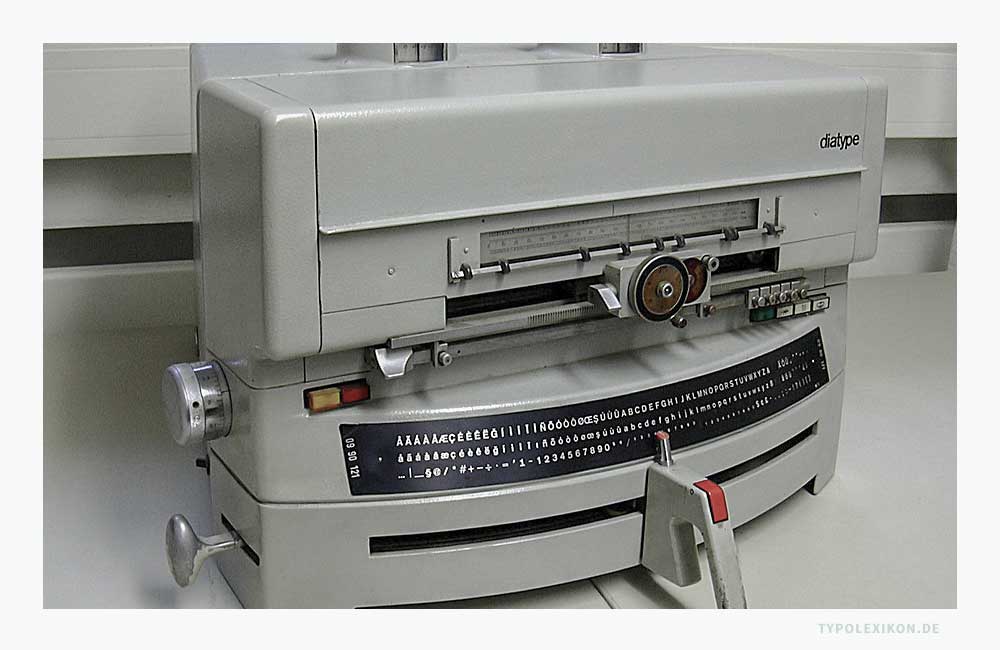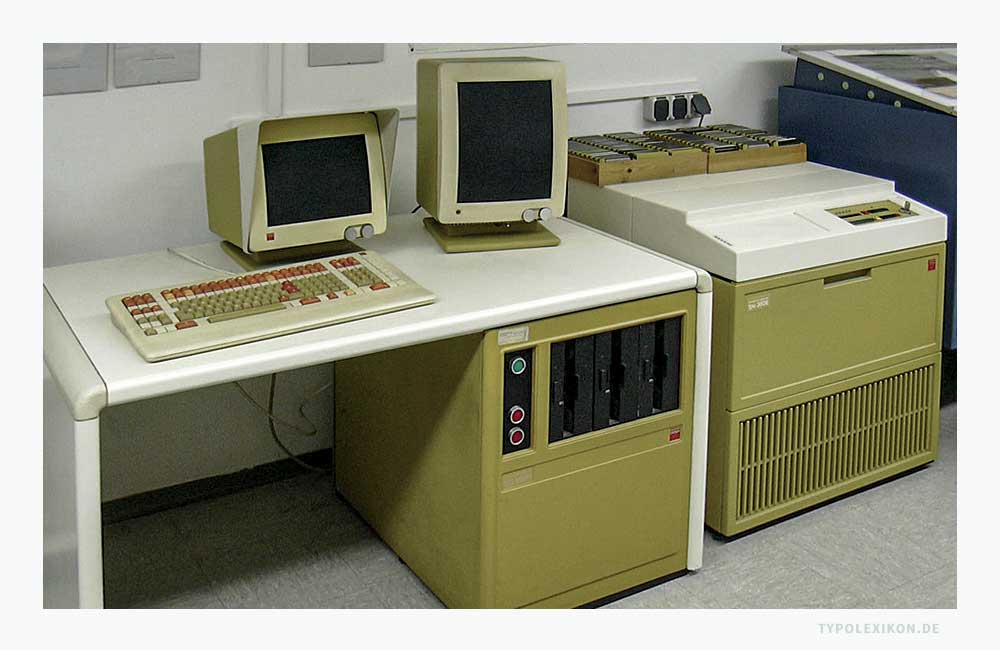
Fotosatz
»Fotosatz« ist eine ugs. Bezeichnung aus dem gewerblichen Sprachschatz dspr. Schriftsetzer und Drucker für den »Optomechanischen Lichtsatz«, einem Verfahren zur Schriftsatzherstellung; alternative Bezeichnung »Lichtsatz«.
Verkürzt formuliert, durchwandert bei optomechanischen, projektionsgesteuerten Fotosatzanlagen der von der Lichtquelle erzeugte Lichtstrahl ein System von Linsen, Spiegeln und Prismen eine Schablone mit der Schrift (Schriftbildträger), um dann auf Fotopapier oder Lithofilm (Abk. Litho) seitenrichtig für den Siebdruck oder seitenverkehrt für den Offsetdruck belichtet und im Anschluss im Nasslabor bzw. später in speziellen Entwicklungsmaschinen entwickelt zu werden. Mit diesen »Lithos« können dann Siebe für den Siebdruck oder Druckplatten für den Offsetdruck belichtet werden.
Fotosatz-Verbundsystem »tps 6300« (Texterfassung und Datenverwaltung) und »tpu 3608« (Belichtungseinheit) der Berthold GmbH. Quelle: Lehrdruckerei des Instituts für Buchwissenschaft, Johannes Gutenberg-Universität Mainz. Foto: Derivat Graph, 2007 gemeinfrei.
Die Belichtung auf einer Fotosetzmaschine erfolgt Schriftzeichen für Schriftzeichen, wobei die Schriftgrade durch Festoptiken oder später, ab den 1980er Jahren, stufenlos durch ein Zoomobjektiv wählbar waren. Ebenso konnten erstmals optomechanisch Zeilenabstände, Schriftlaufweiten, Schriftlagen, Schriftstärken und Schriftbreiten stufenlos verändert werden, was allerdings aus Sicht der Mikrotypografie zu qualitativ minderwertigen Satzergebnissen führte. Beispielsweise war es nun technisch möglich, Schriften optisch zu verzerren, zu dehnen, zu verdicken oder zu stauchen, was allerdings der Lesbarkeit und der Ästhetik in vielerlei Hinsicht nicht unbedingt förderlich war.
Mit der Einführung des Fotosatzes verzichteten weltweit Buch- und Zeitungsverlage auf die Verwendung von typografischen Ligaturen, denn diese waren technisch nun nicht mehr notwendig und der Werksatz wurde dadurch deutlich günstiger. Infolge veränderten sich auch die Lesegewohnheiten der Rezipienten.
Historie
Der Fotosatz wurde ursprünglich Ende des 19. Jahrhunderts für Flachdruckverfahren, speziell für den Tiefdruck und Offsetdruck entwickelt. Die ersten Patente erhielt 1893 der Engländer Arthur Ferguson und der 1894 der Ungar E. Porzsold. 1)
Die ersten Fotosetzmaschinen in Deutschland kamen Ende der 1950er Jahre zum Einsatz, beispielsweise die halbautomatische und mechanisches »Diatype« von Hugo Heine, die er zwischen 1952 und 1960 im Auftrag der Schriftgießerei H. Berthold AG (siehe Hermann Berthold) 2) entwickelt hatte und die 1958 – kurz vor dem hundertjährigen Jubiläum der H. Berthold AG – auf der Drupa in Düsseldorf, der weltgrößten Messe der Druck- und Druckmedienindustrie, vorgestellt wurde.
Fotosatzgerät Diatype der H. Berthold AG. Quelle: Lehrdruckerei des Instituts für Buchwissenschaft, Johannes Gutenberg-Universität Mainz. Foto: Derivat Graph, 2007 gemeinfrei.
In den nachfolgenden Jahren bis Ende der 1990er Jahre produzierten unterschiedliche Hersteller, unter ihnen auch die Linotype GmbH, 3) unterschiedliche Arten von Fotosetzmaschinen, die den materiellen Schriftsatz mit physischen Drucktypen aus Metall (z.B. aus einer Blei-Zinn-Antimon-Kupfer-Legierung) in der BRD (Westdeutschland), Österreich und der Schweiz ab den 1970er Jahren sukzessive ablösten und den Schriftsatz, die Druckvorstufe (Prepress) und das gesamte polygrafische Gewerbe (Druckwesen) revolutionierte und völlig neu strukturiere. Darüber hinaus brachte der Fotosatz für das Grafikdesign und Editorial Design mehr gestalterische Freiheiten und löste – außer in der DDR (Ostdeutschland) – den materiellen Schriftsatz nahezu komplett ab. Althergebrachte Berufe gingen verloren, völlig neue Berufsbilder, Maschinen und Firmen entstanden, so auch viele eigenständige Fotosetzereien.
Ab 1982 revolutionierte das »Desk Top Publishing« (DTP), das Anfang der 80er Jahre von Paul Brainerd (*1948) mit der Software Page-Maker® für den Apple Macintosh (Mac) von Apple® Inc. (USA) entwickelt wurde, ab Ende der 80er Jahre die gesamte Typografie. Der Personal Computer löste den Fotosatz in kürzester Zeit ab; wieder entstanden neue Medien, Berufe, Firmen, Ausbildungsstätten und Betrachtungsweisen. 4)  5) 6)
Die Ära des angewandten Fotosatzes dauerte im Wesentlichen nur knapp vier Jahrzehnte.
↑1 Quelle: Welke, Martin und Boris Fuchs: Zeitungsdruck, Die Entwicklung der Technik vom 17. zum 20 Jahrhundert, KG Saur, München 2000, ISBN 3-598-21321-2.
↑2 Anmerkung: Die Berliner Berthold AG wurde im II. Weltkrieg weitgehend durch Bomben zerstört. Sie zog in den 1980er Jahren vom Mehringdamm in Berlin-Kreuzberg in die Teltowkanalstraße in Berlin-Lankwitz. 1964 kaufte Berthold die Firma »Film-Klischee« in Taufkirchen bei München, die das Titelsatzgerät »staromat« für den Fotosatz herstellte. Dorthin wurde dann auch die Schriftträgerfertigung für Fotosatzschriften verlegt (Quelle: Eric Spiekermann in einer E-Mail vom 18.5.2020 an Wolfgang Beinert). Künstlerischer Leiter war dort der Typograf Günter Gerhard Lange. Im Zuge der Digitalisierung ging die H. Berthold GmbH 1993 in Konkurs. Ein Rechtsnachfolger der Berthold GmbH existiert nicht, auch wenn dies der eine oder andere Schriftenhändler beteuert.